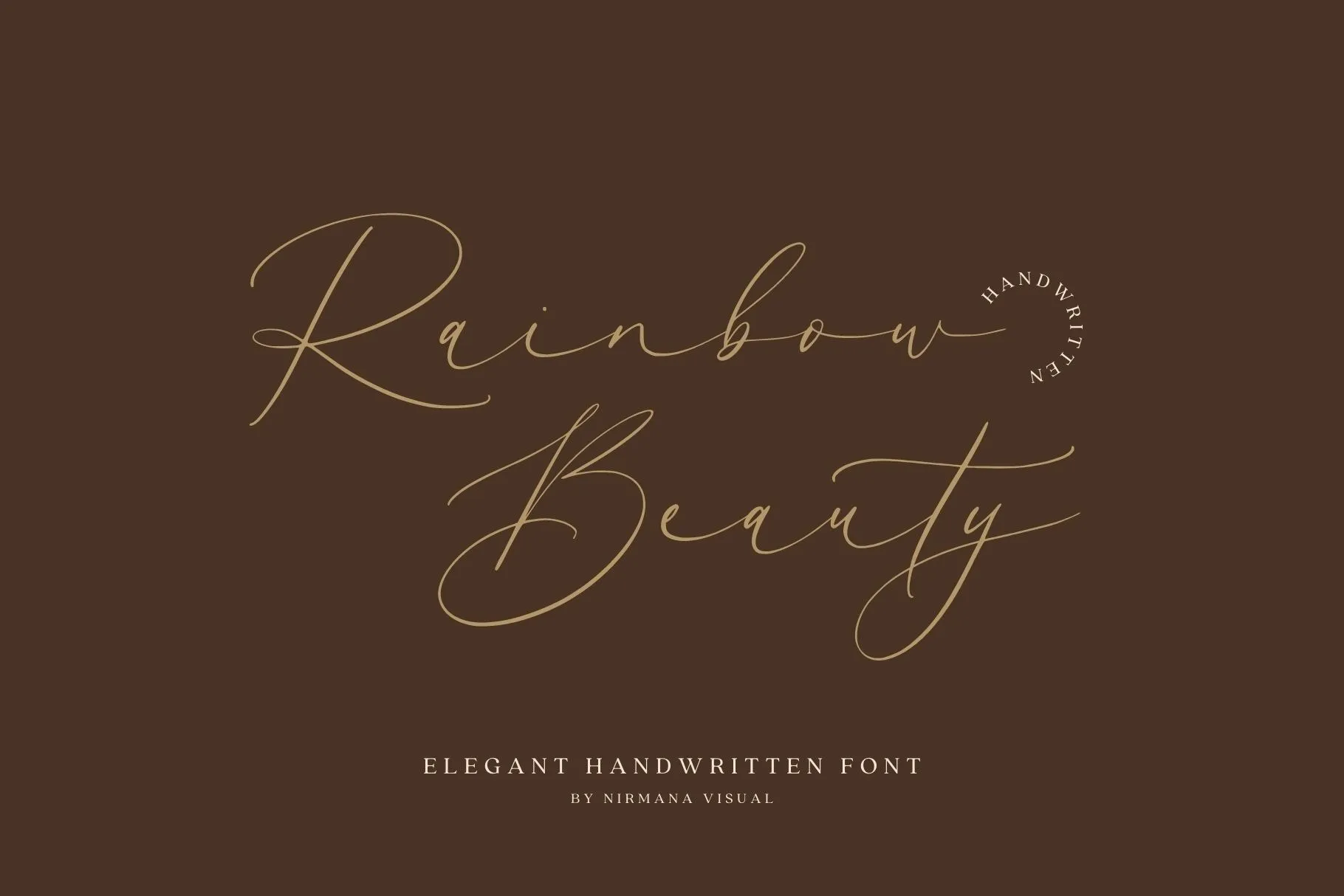
Esta fonte foi criada para imitar a escrita manual com uma forma moderna e única do caligrafia. Seu estilo de escrita é extremamente natural e perfeito para trabalhos de design contemporâneos. A Rainbow Beauty possui um estilo único de caligrafia, sendo especialmente adequado para uso em trabalhos comerciais e casamentos. Suas linhas elegantes e fluidas se destacam com uma facilidade notável na sua aplicação, tornando-a uma escolha óbvia para cartões de visitas e até mesmo para a decoração dos convites de casamento mais sofisticados. Essa fonte é perfeita para designers que desejam adicionar um toque autêntico ao seu trabalho, sem sacrificar o modernismo e sofisticação que se espera em design atual.